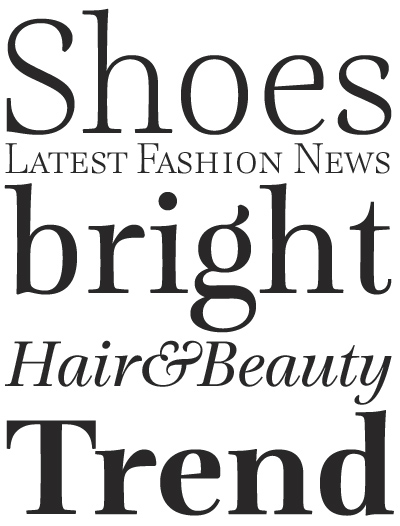
El diseñador Ramiro Espinoza nos presenta su última creación Lavigne Display. Se trata de la primera entrega de una familia tipográfica cuya intención es aportar un toque de distinción allí donde sea utilizada.
Sus estilizados trazos, con un evidente aroma caligráfico, unidos a sus finos remates y su generoso ojo medio proporcionan al texto un aspecto refinado y sofisticado del que se beneficiarán, sin duda, todo tipo de publicaciones que aspiren a reflejar un cierto status en sus páginas.
Con un rango de estilos que cubren cualquier necesidad de jerarquización tipográfica, Lavigne Display se presenta en formato OpenType y a la romana y la itálica la acompañan versalitas y cuatro juegos de figuras.